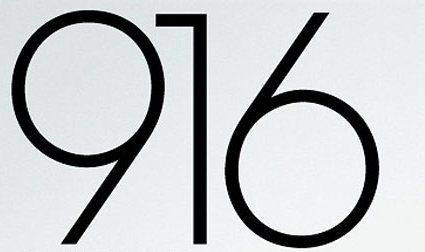
Ähnlich Futura, Avangard, Century Gothic
Hallo ich suche genau diese Schrift (siehe Anhang)
Es ist kein Futura-, Avangard- oder Century Gothic - Schnitt.
Soweit bin ich schon mal.
Weiß jemand rat?
Das gerade abgeschnittene C (auch S, …) und das spitze A (Auch N, M, V) sind charakteristisch.
?? Das C und das S in CHELSEA und CLINTON gibt es nicht in die Futuras die ich kenne … Ein spitzes A und N wie in CHELSEA und CLINTON schon. AN INSIDE LOOK sieht wiederum aus wie Futura und die Zahlen sehen aus wie ITC Avant Garde Gothic. Die Chalet ist eine Art von Remix von Schriften wie ITC Avant Garde, ITC Bauhaus usw. habe sie jetzt nicht genau angeschaut aber es kann also sein, dass die Zahlen da auch so aussehen.
Aber wie Robert M. schon sagte, es könnte eine Kombination verschiedener Schriften sein.
stark. nicht schlecht die gedanken.
leider passt auch diese kombination nicht.
die Chalet ist im C ein gutes stück geschlossener und das S ist auch recht anders. die punzen der ziffern sind auch ein bisschen zu groß. interessant: die gesuchte typo hat gerade stamme beim M. wodurch die Futura auch rausfällt.
tricky. and the search goes on.
Stimmt! Ich muss gestehen, dass ich die Harmonia Sans noch nie gesehen habe. Wobei ich ehrlich gesagt nicht das Gefühl hatte, damit etwas verpasst zu haben. Aber A und N fehlen leider die Spitzen. Customized Font?